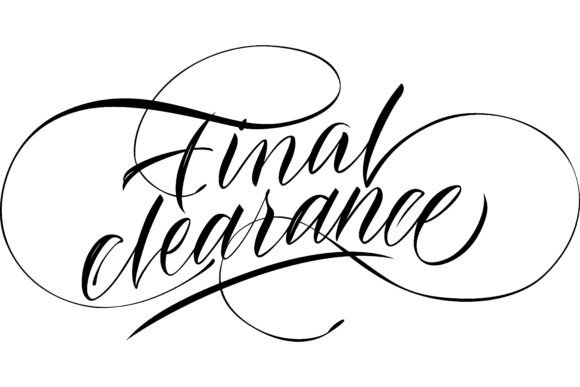
Final Clearance Lettering. Calligraphic
การค้นหาองค์ประกอบการออกแบบที่เหมาะสมอาจเป็นเรื่องท้าทาย แต่ Final Clearance Lettering. Calligraphic นำเสนอคอลเลกชันที่โดดเด่นซึ่งช่วยยกระดับงานของคุณได้ทันที
ไม่ว่าคุณจะสร้างผลิตภัณฑ์ POD (Print on Demand) คำเชิญงานแต่งงาน หรือกราฟิกโซเชียลมีเดีย Final Clearance Lettering. Calligraphic ก็เหมาะสมอย่างยิ่ง